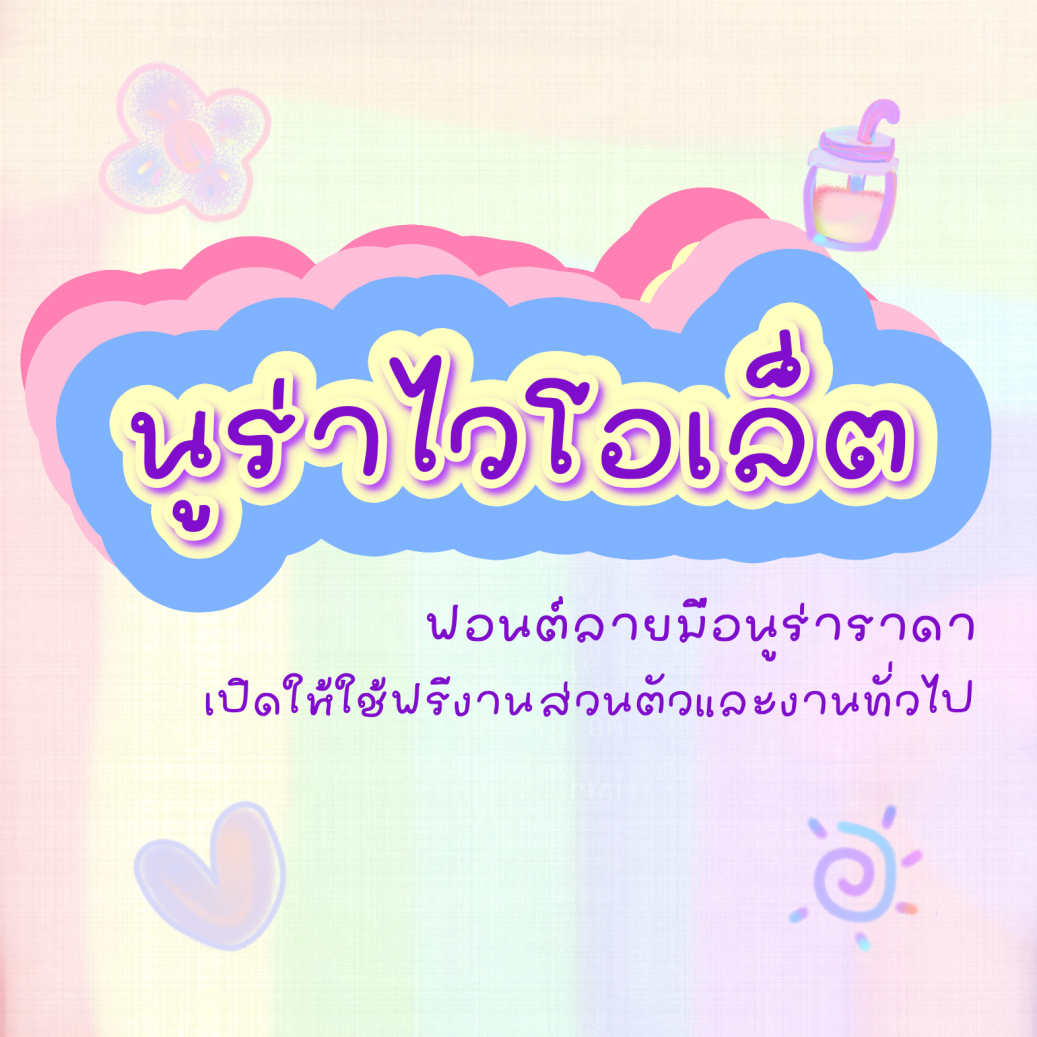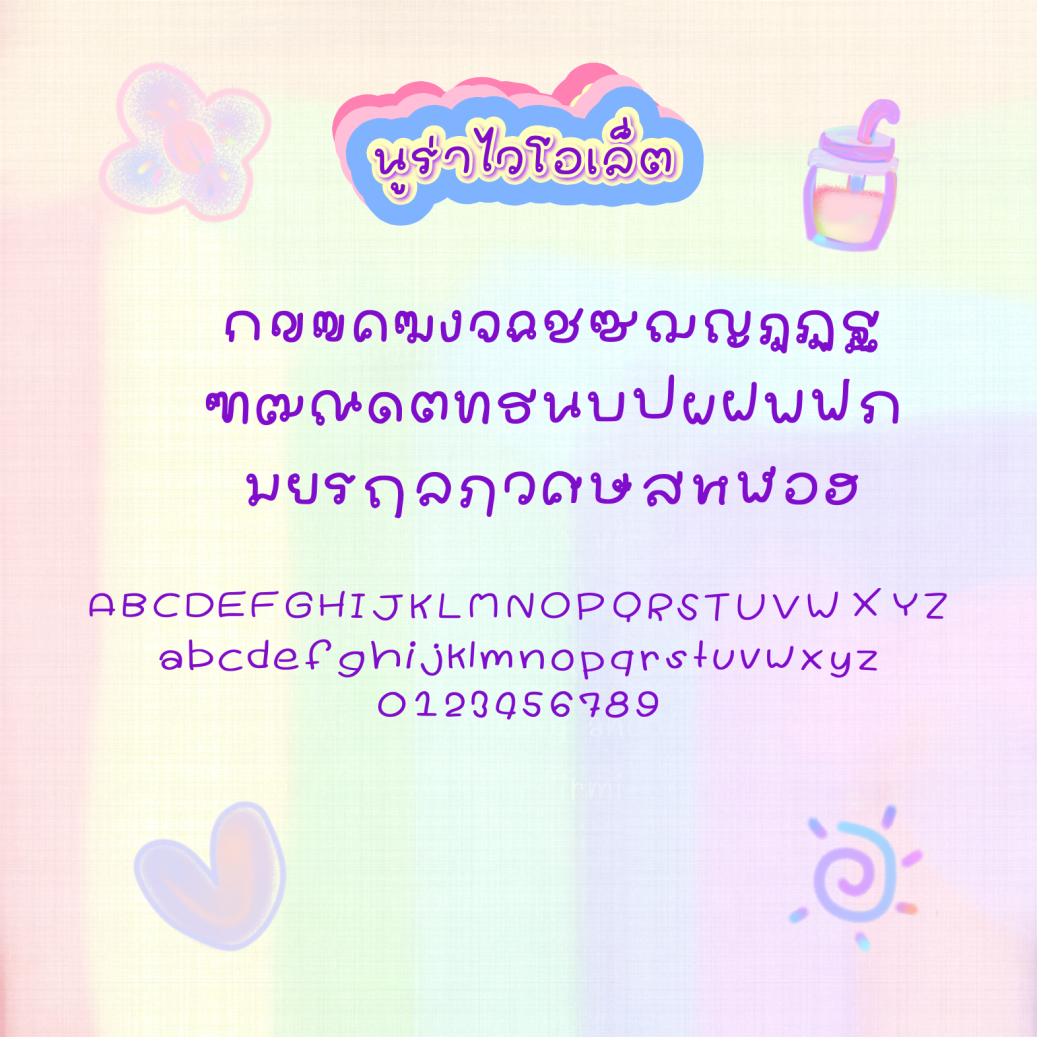
นูร่าไวโอเล็ต (Nura violet)
ฟอนต์นูร่าไวโอเล็ต (Nura violet)
ฟอนต์ลายมือน่ารัก ฟอนต์มีหัว อ่านง่ายตัวกว้างเล็กน้อย   เหมาะจดโน๊ต  ทำโปรโมทสินค้า มีด้วยกัน  3 น้ำหนัก  คือ บาง ปกติ หนา